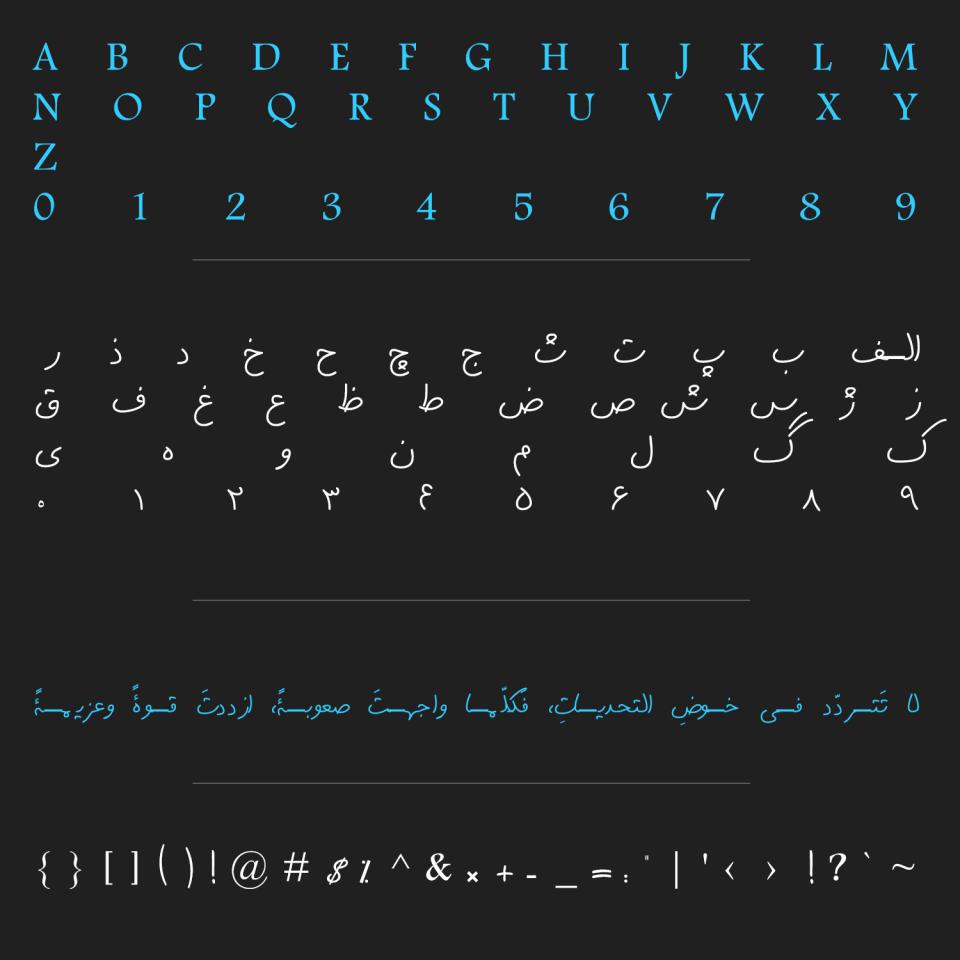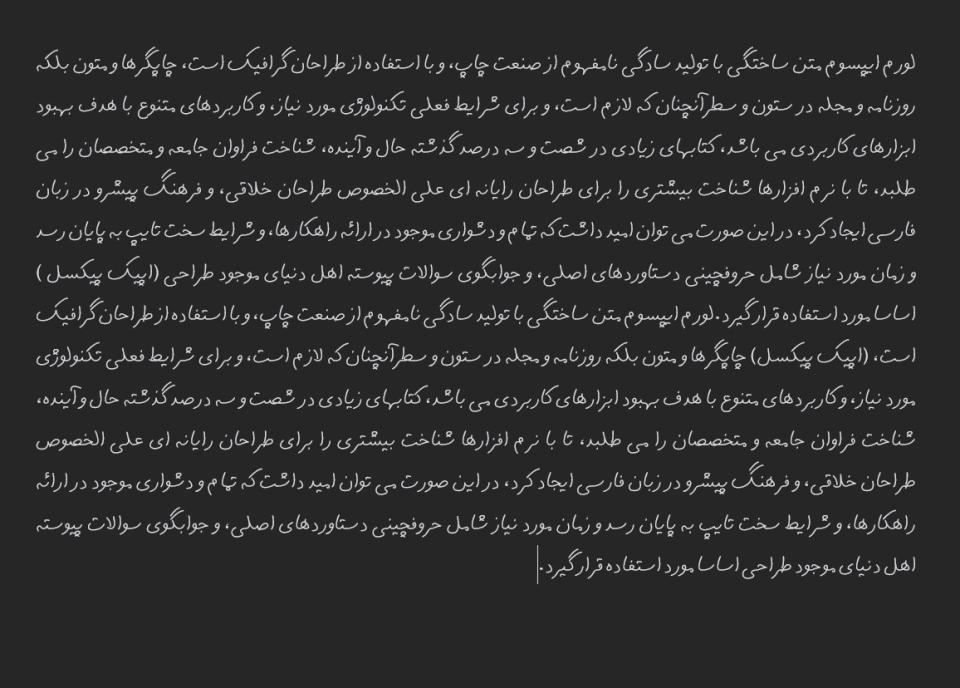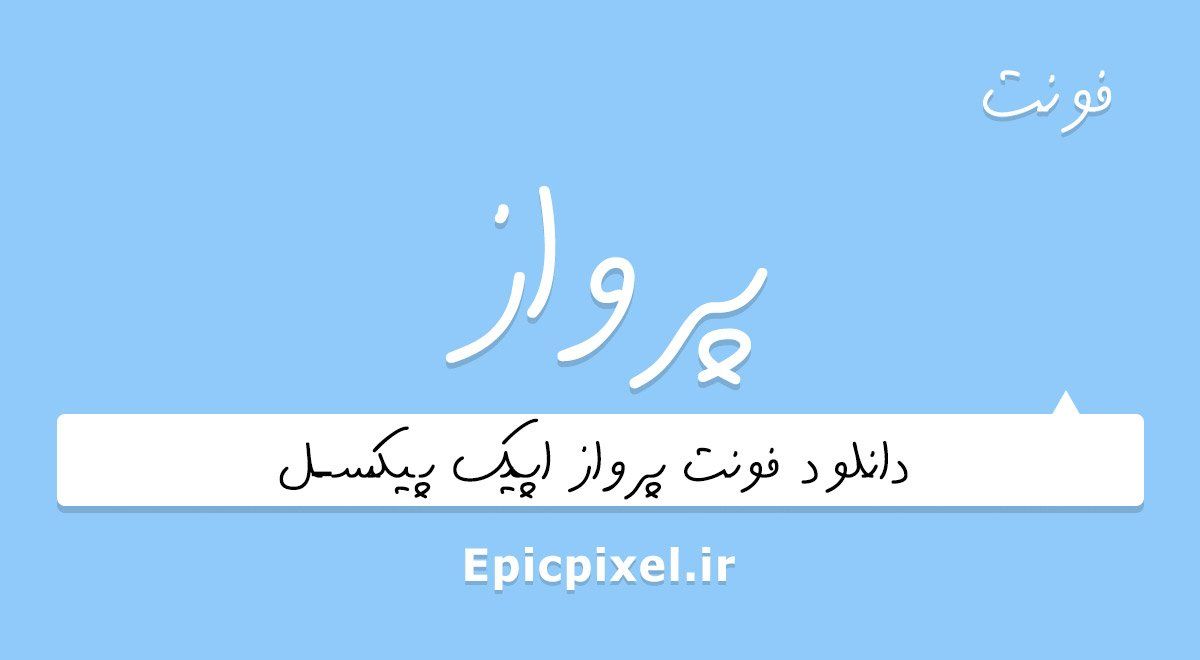
3 فونت پرواز فارسی Parvaz
فونت فارسی پرواز یک فونت دست نویس ، با وجود رایگان بودنش، یکی از محبوب ترین انتخاب ها برای طراحان و کاربران فارسی زبان است. این فونت به دلیل طراحی خاص و خوانایی بالایش، در طیف وسیعی از پروژه ها، از طراحی وبسایت و اپلیکیشن گرفته تا تولید محتوای چاپی و گرافیکی، کاربرد دارد.
یکی از ویژگی های برجسته فونت پرواز، ظاهر دست نویس و صمیمی آن است که حس گرما و صمیمیت را به مخاطب منتقل می کند. این ویژگی، به ویژه در طراحی هایی که نیاز به ارتباط نزدیک با مخاطب دارند، بسیار مؤثر است. همچنین، این فونت سه مدل مختلف ( F , W , Normal ) برخوردار است که به طراحان امکان می دهد تا در طراحی های خود، به راحتی از وزن های مختلف آن برای ایجاد تأکید و تمایز استفاده کنند.
با این حال، باید به این نکته نیز اشاره کرد که فونت پرواز، با وجود محبوبیتش، ممکن است برای متن های طولانی و رسمی، انتخاب چندان مناسبی نباشد. ظاهر دست نویس آن، ممکن است در این نوع متن ها، خوانایی را کمی کاهش دهد. اما برای عناوین، تیترها، لوگوها و طراحی های خلاقانه، یک انتخاب عالی و رایگان به شمار می رود. به همین دلیل، اگر به دنبال فونتی هستید که هم رایگان باشد، هم ظاهر جذاب و مدرنی داشته باشد و هم در پروژه های گوناگون قابل استفاده باشد، فونت پرواز می تواند گزینه ی ایده آلی برای شما باشد.